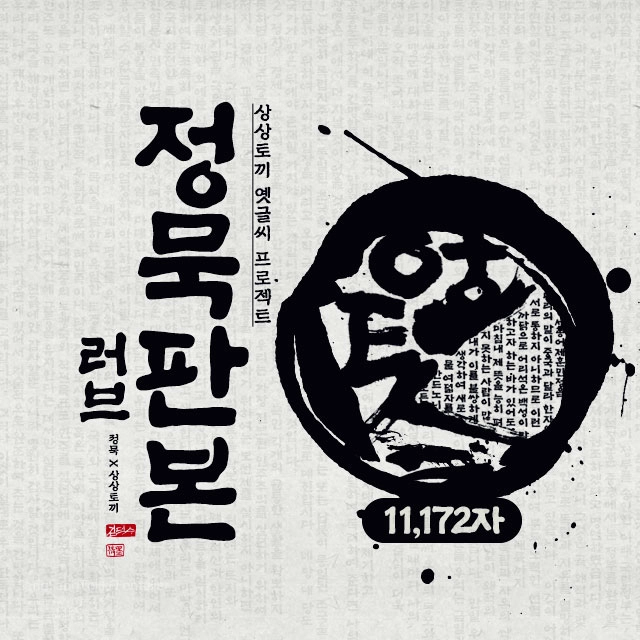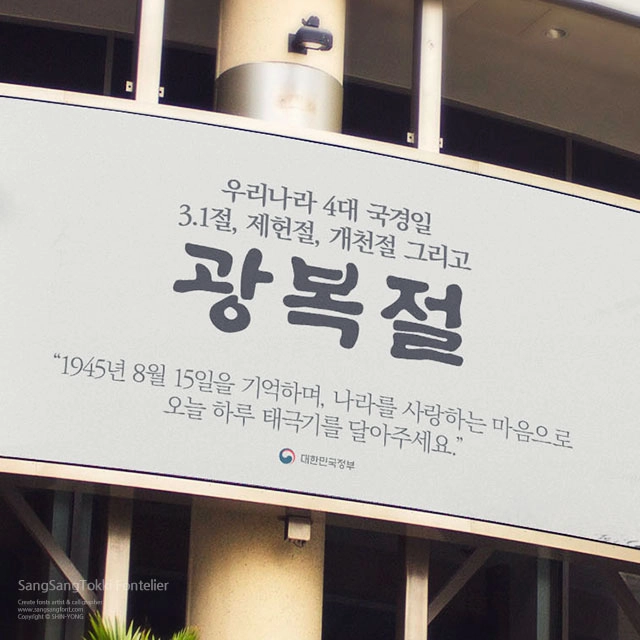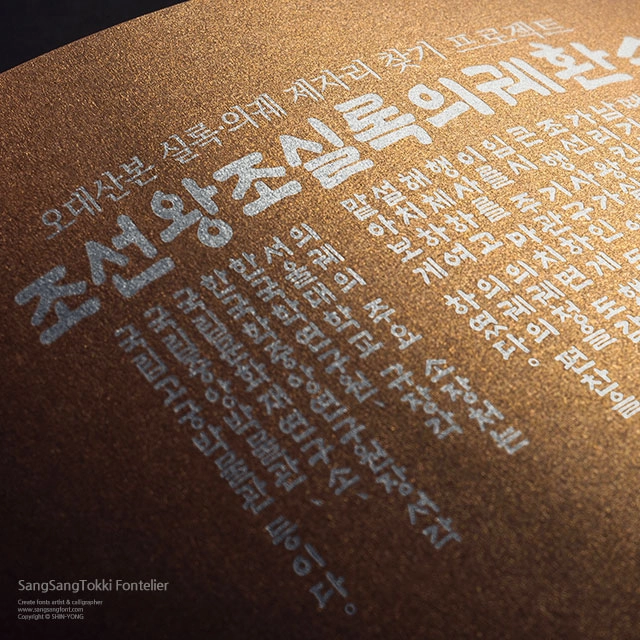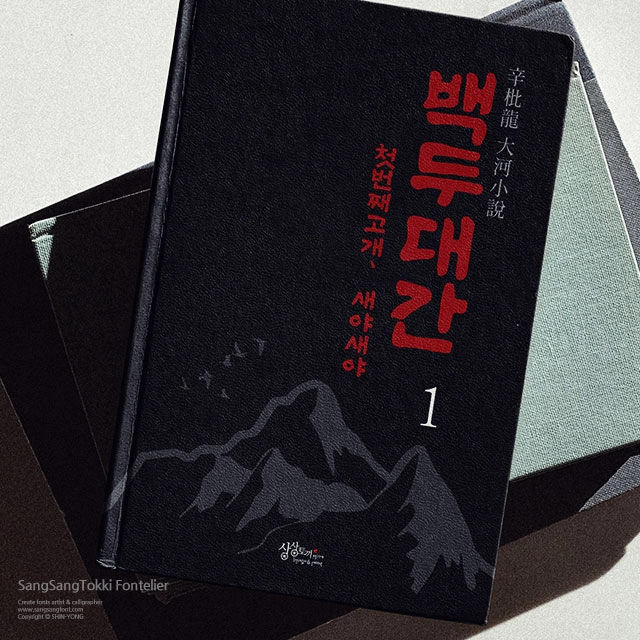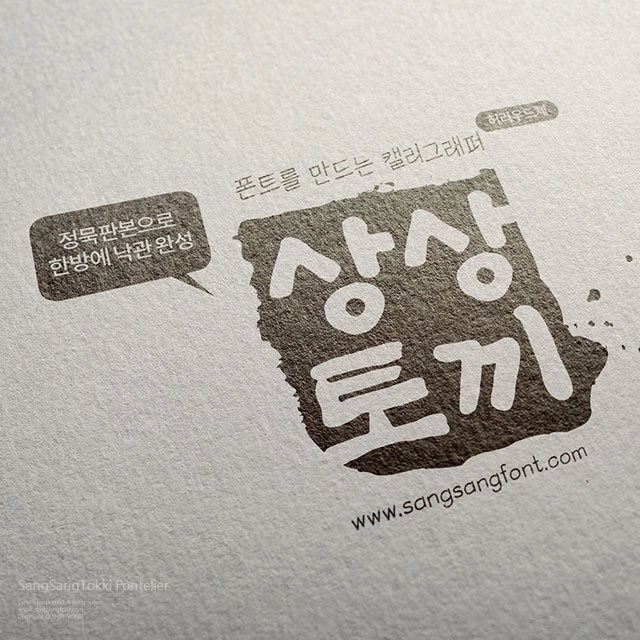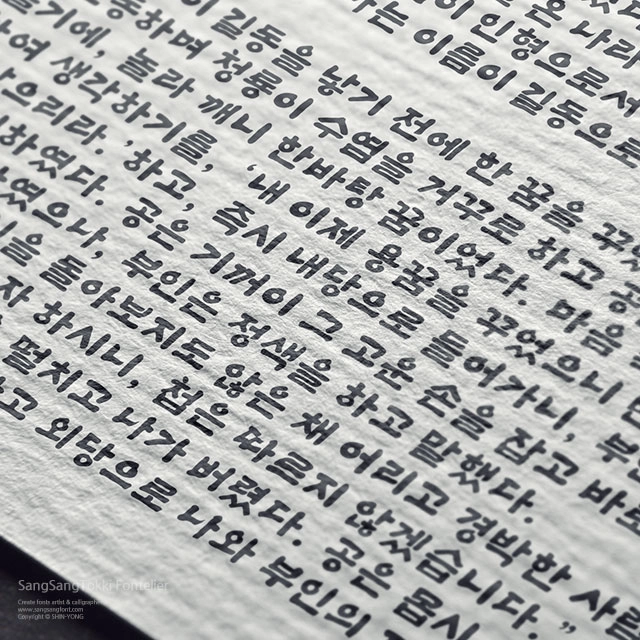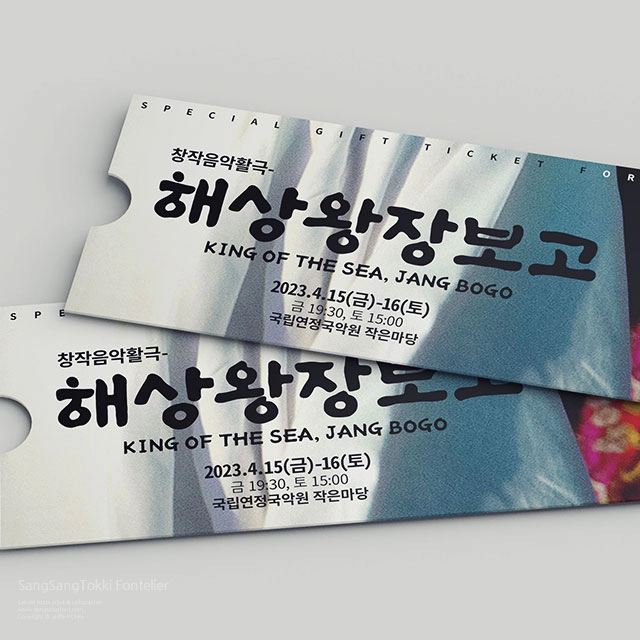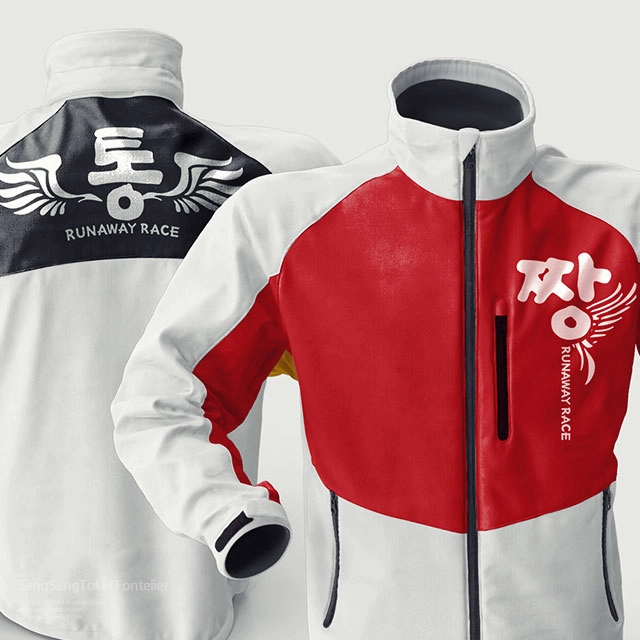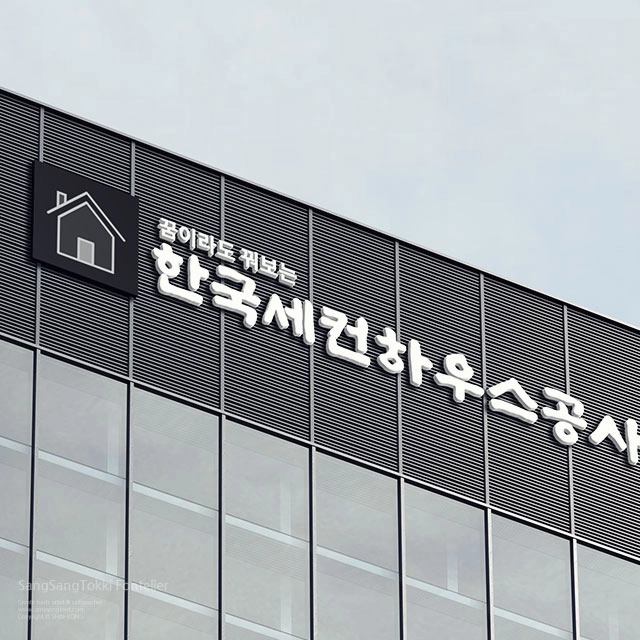
정묵 판본 Love (세로쓰기 전용폰트 포함)
상상토끼와 정묵 작가의 네번째 콜라보레이션 작업으로 탄생한 옛글씨 캘리그라피 폰트, 와일드 버전의 거친 붓질감을 부드럽게 굴린 말랑말랑한 판본체, 정묵 판본 Love (세로쓰기 전용폰트 포함)
한글 11,172자 / 영문 52자 / 약물 84자
정묵판본 Love 가로+세로 각 1종